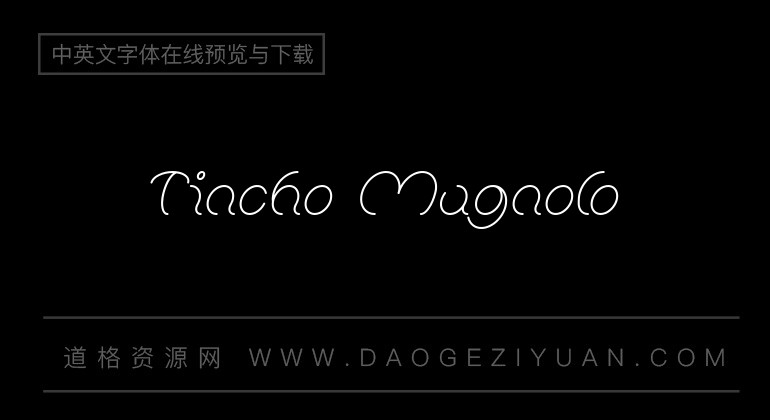
Tincho Mugnolo
Tincho Mugnolo 字体是一款现代简约风格的字体,由著名设计师 Tincho Mugnolo 创作。这款字体以简洁明快的线条和节奏著称,具有极强的可读性和灵活性,适用于标题、标签和短文本。Tincho Mugnolo 字体的特点是圆润的字母形状和流畅的笔画,使其具有温暖、友好的感觉,适用于各种类型的文本,特别是现代简约风格的文本。
Tincho Mugnolo是一款非常不错的手写艺术字体,具有很好的视觉感,适合于文化类的宣传设计、商业类品牌的广告和产品包装设计以及个性化文字排版等较多场景。
Tincho Mugnolo字符映射图